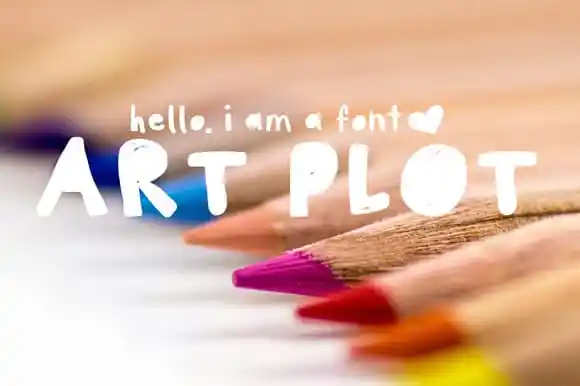
NEW Art Plot – Hand Drawn Font – Download Grátis
A nova fonte ‘NEW Art Plot – Hand Drawn Font’ é perfeita para aqueles que desejam dar vida à sua arte digital com uma mão humana e artesanal. Especificamente projetada para a categoria de fontes Display, esta criativa novidade vem da autoria do designer Hamilton. Com seu traço suave e vibrante, NEW Art Plot captura as nuances sutis dos desenhos manuais, oferecendo um estilo único capaz de destacar qualquer obra. Suas linhas curvadas e bordas suaves são perfeitas para adicionar uma atmosfera nostálgica e artística à sua próxima criação digital. A fonte combina a precisão precisa das fontes display tradicionais com o charme desenho livre de um artista, tornando-a ideial não apenas para aplicativos digitais, mas também para design gráfico em papel. Para os amantes da arte e do design, NEW Art Plot é mais que uma fonte; ela é uma expressão de habilidade, criatividade e paixão. Com sua capacidade única de traduzir um estado de espírito artisticamente autêntico no meio digital, esta fonte é perfeita para aqueles buscando trazer a arte manual em sua próxima produção gráfica.